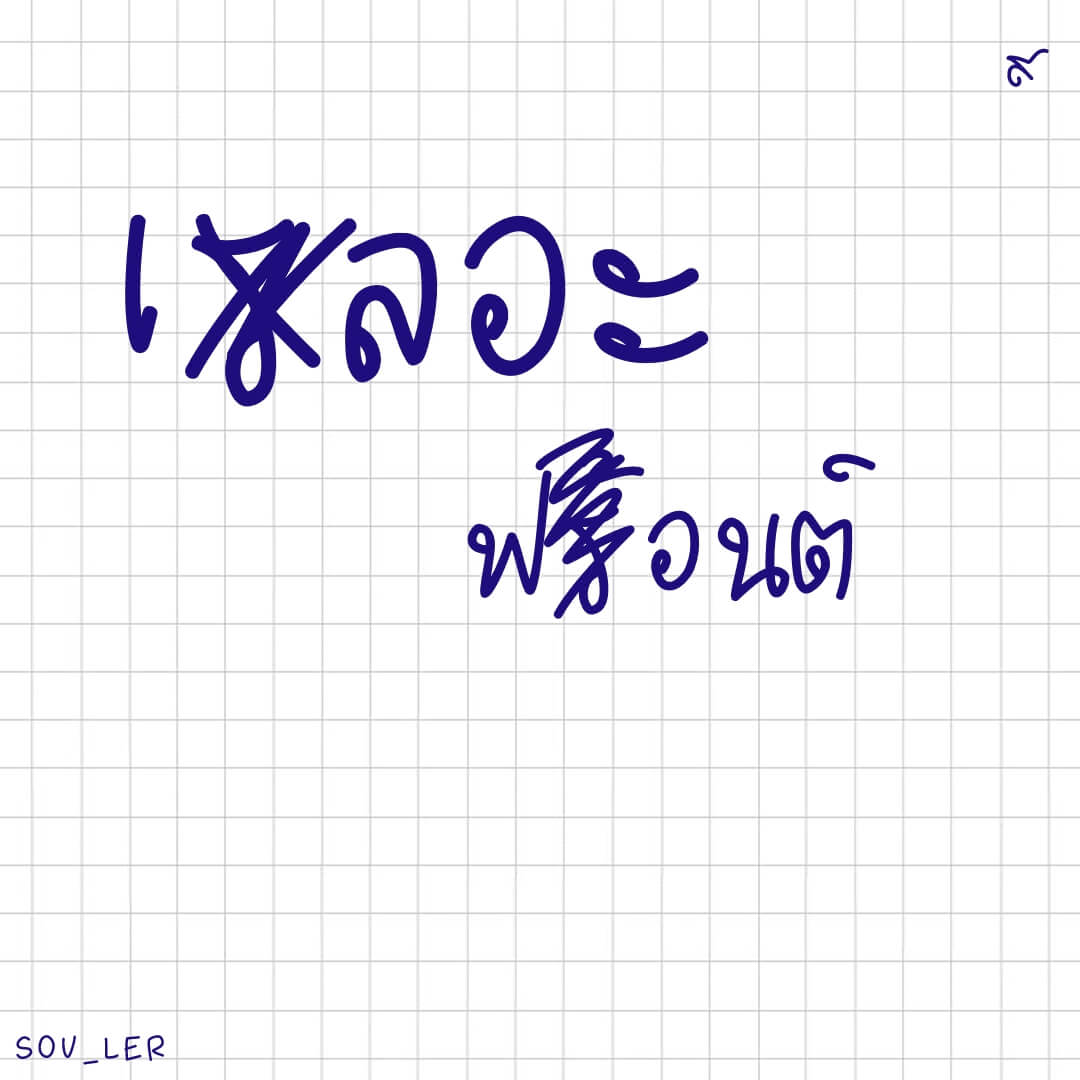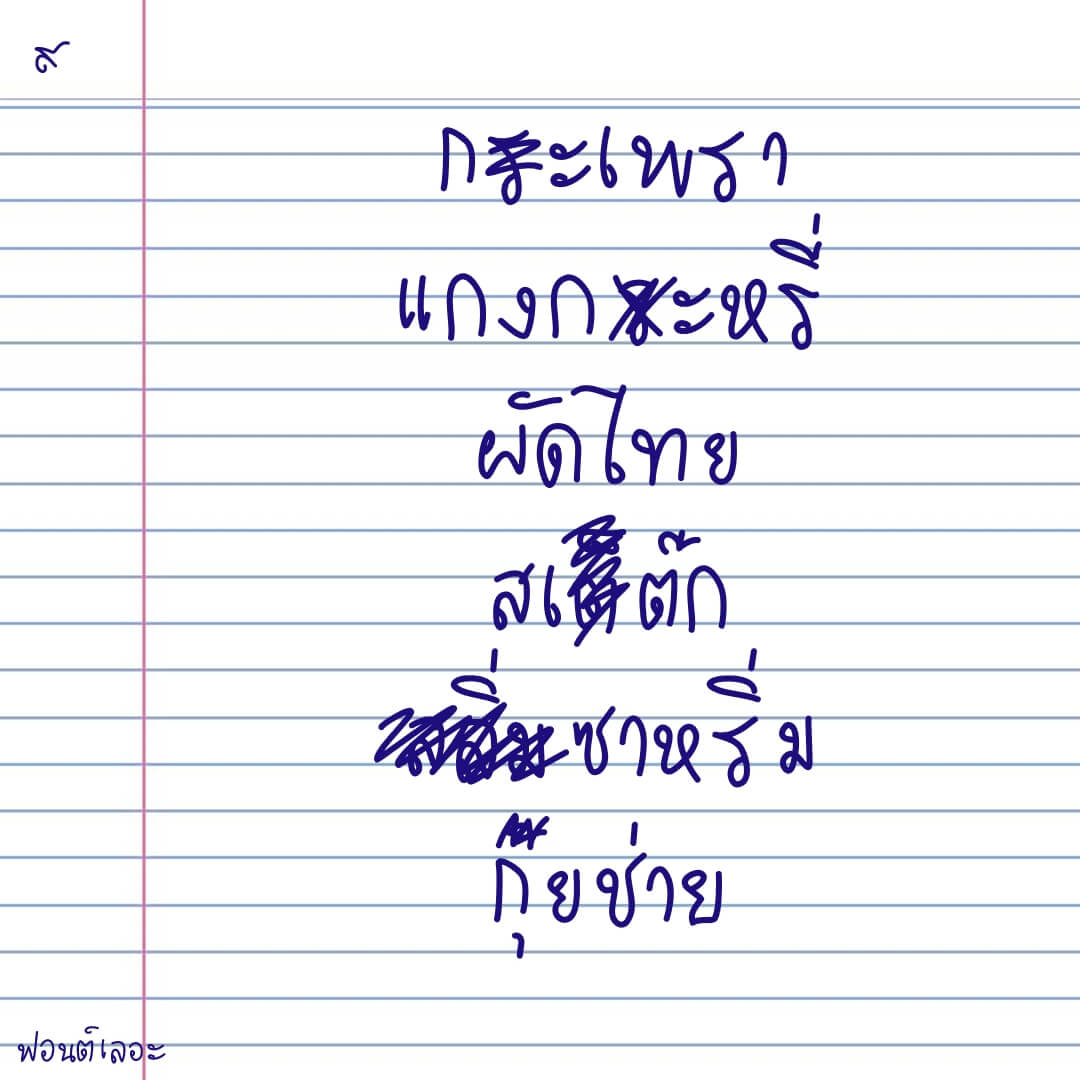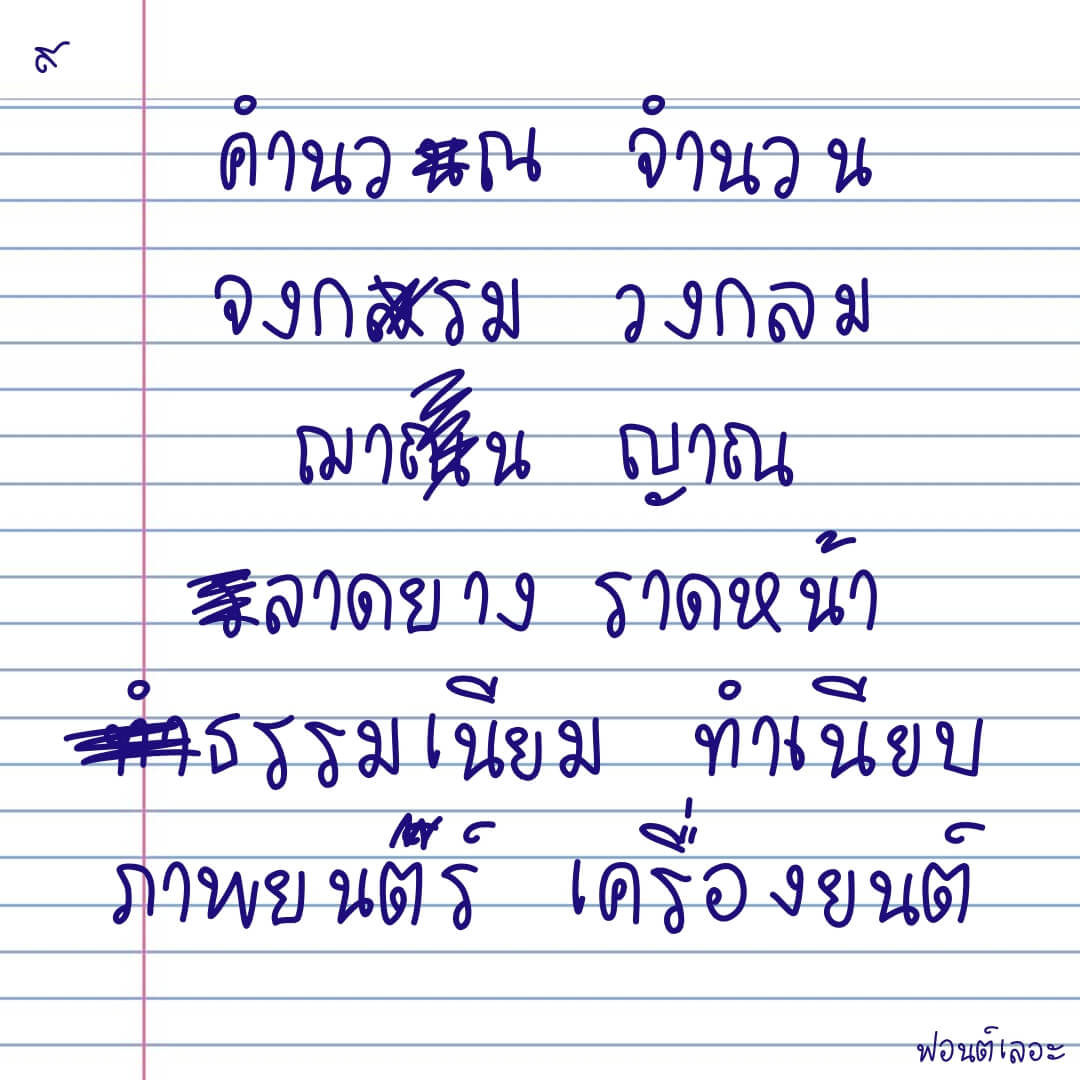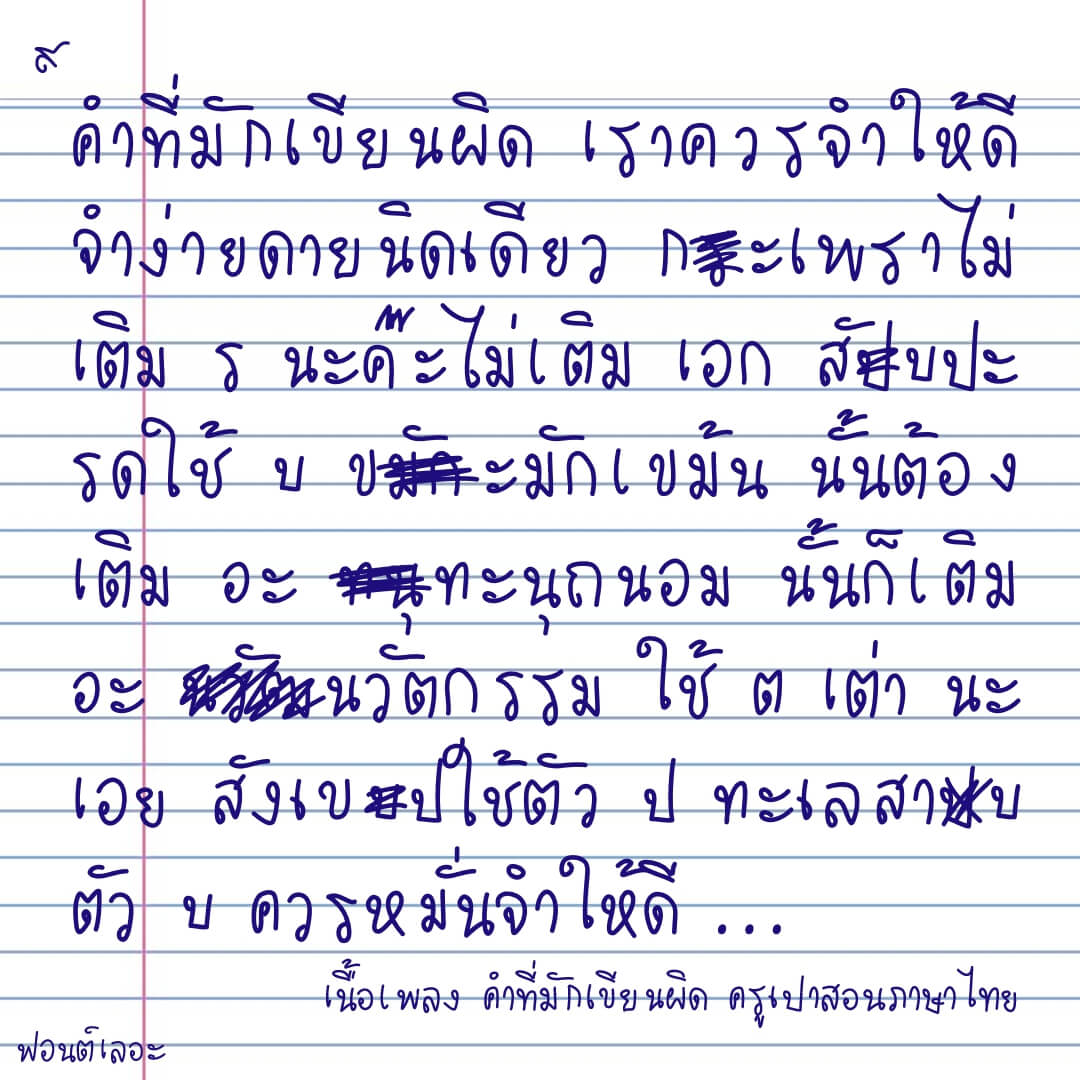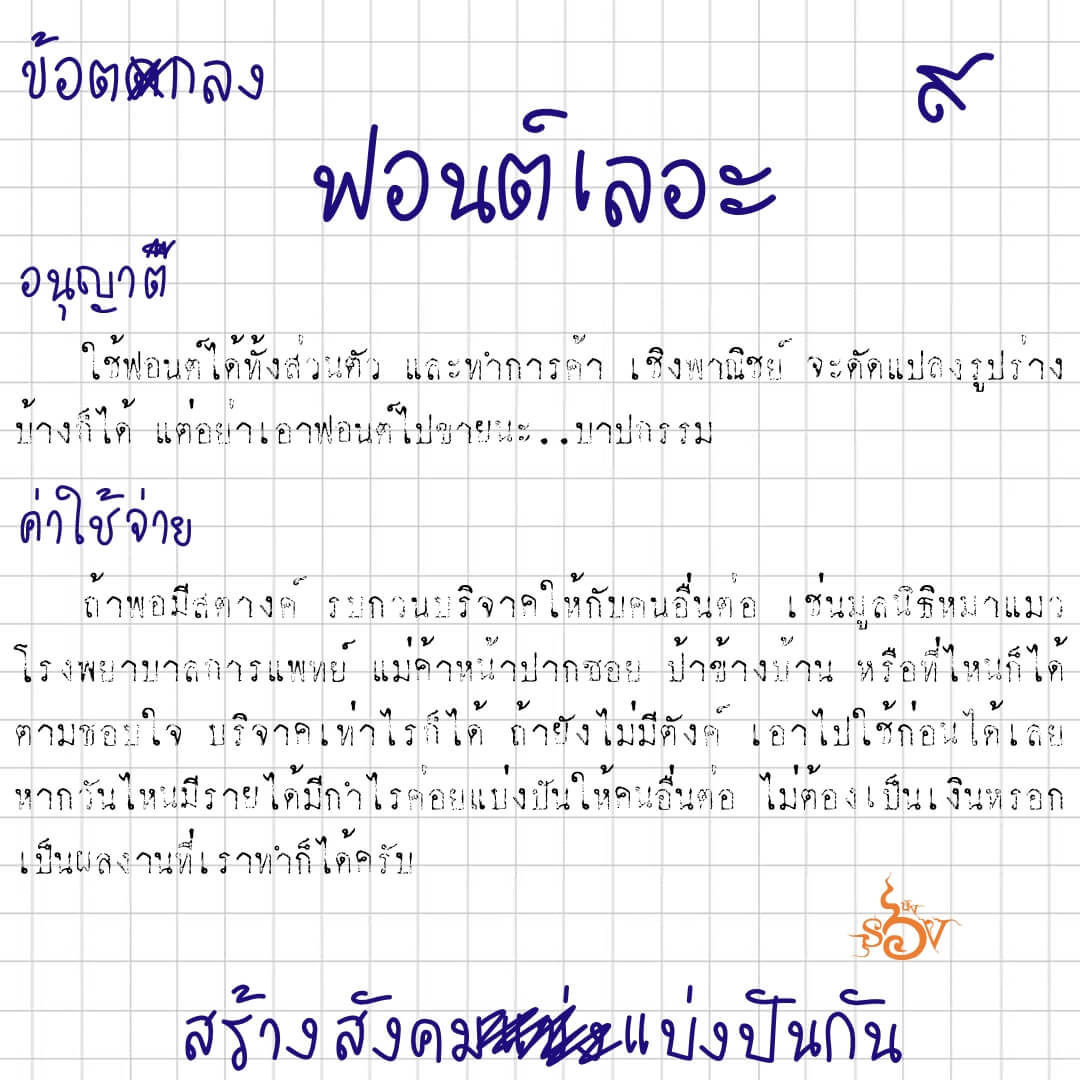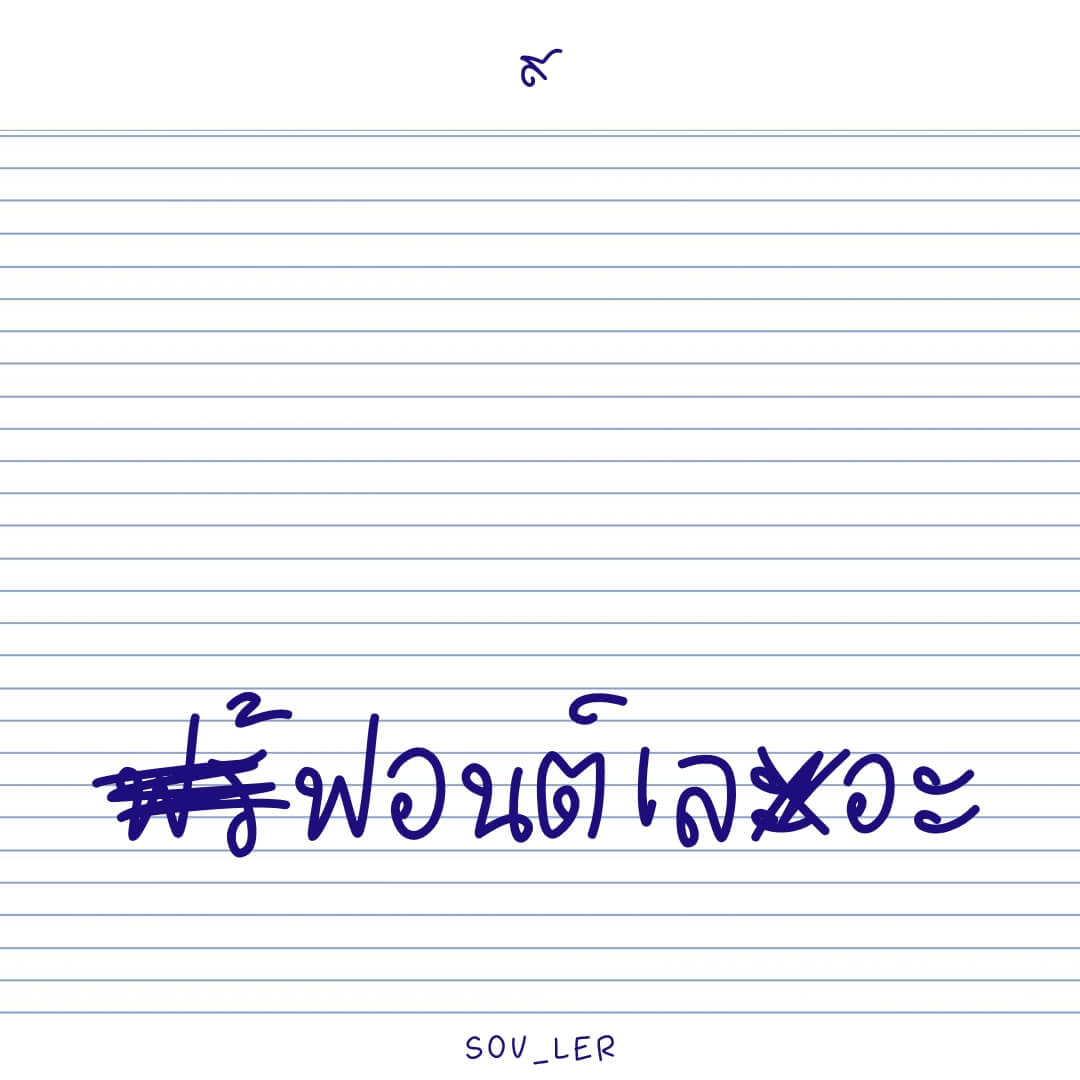
ฟอนต์เลอะ เมื่อยางลบหมึกทำกระดาษเป็นรู ส่วนลิควิดก็ยังไม่มา ขีดฆ่านี่แหละเวิร์ก… แต่มันจะทำให้สมุดจดดูเลอะเทอะมาก
วิธีใช้ กด “-” หลายๆตัว ถ้าไม่ได้ผล กด “ฯ” แทน
เลอะ (SOV_ler)